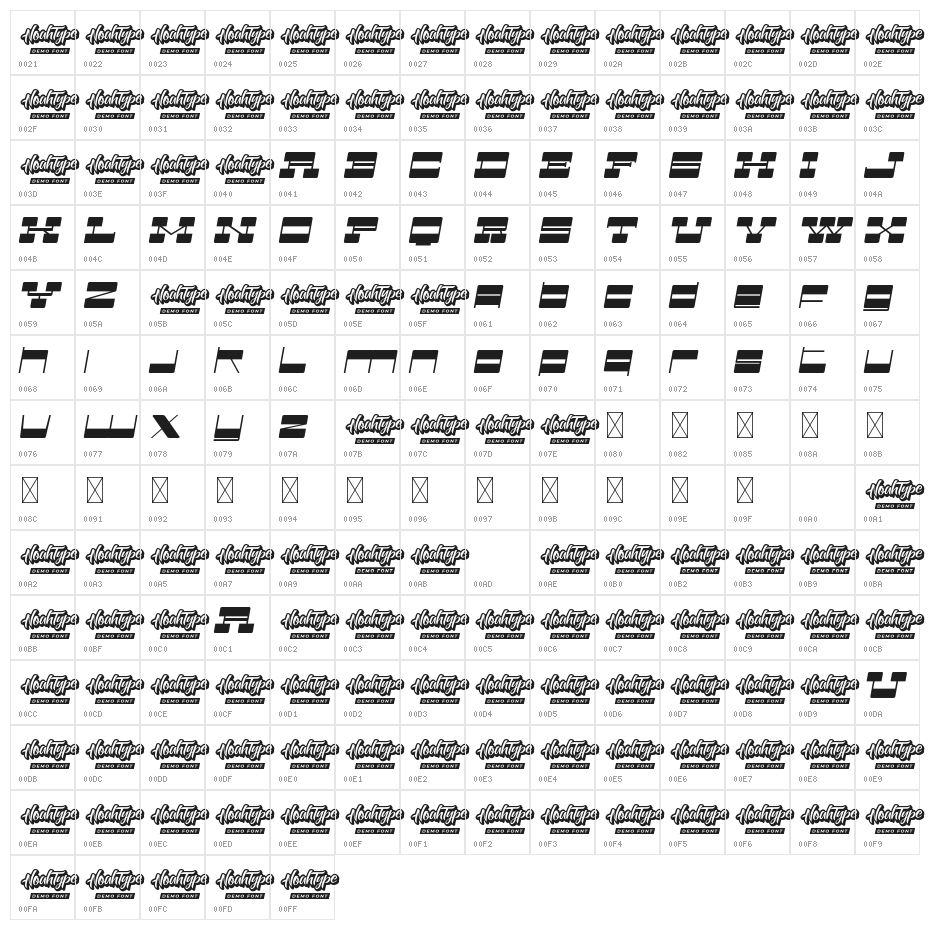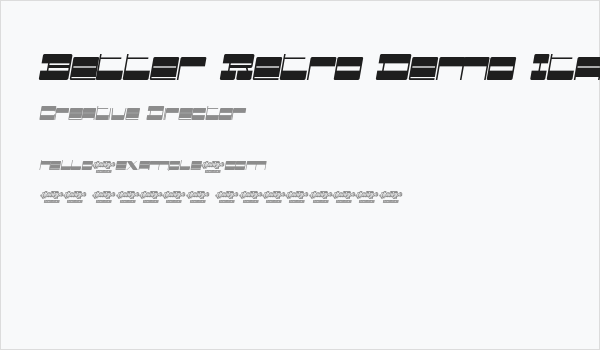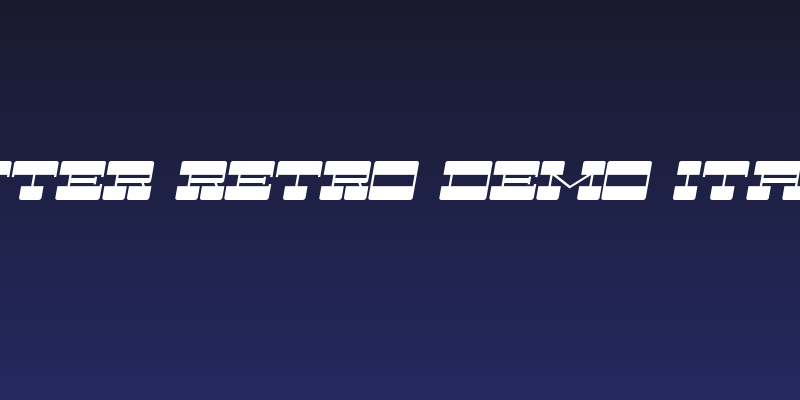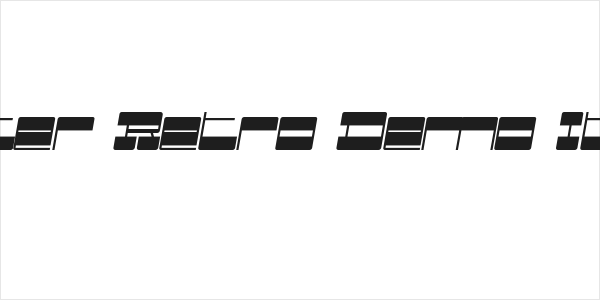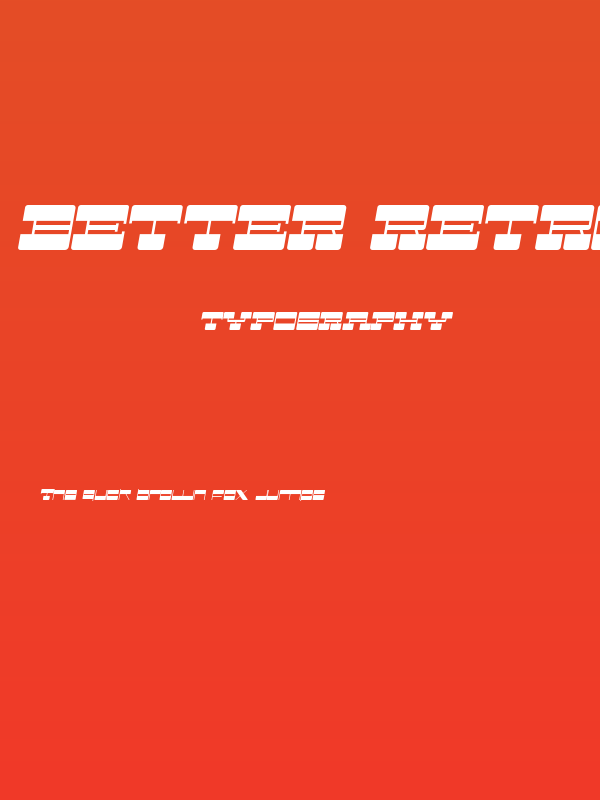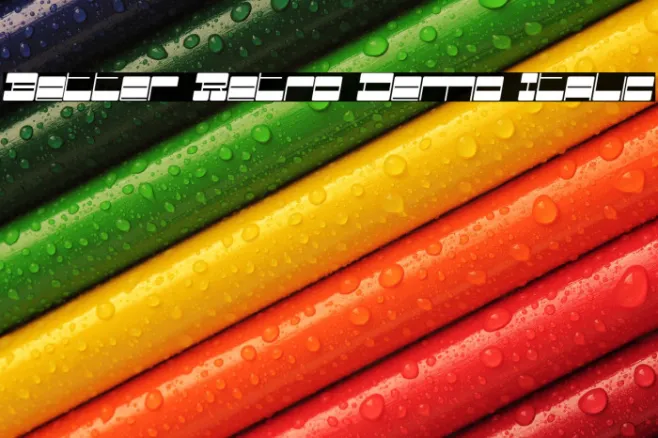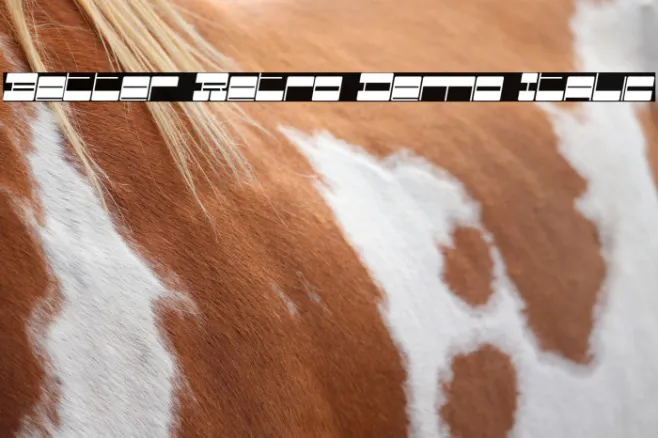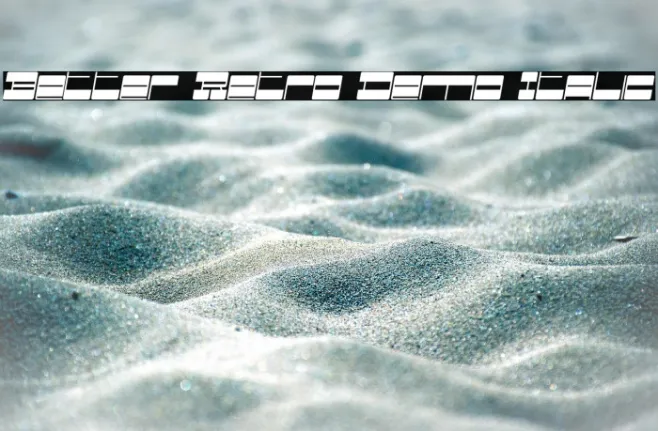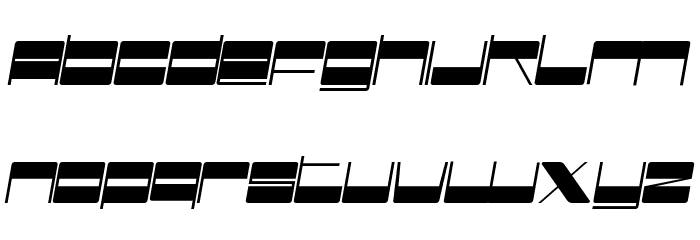
Better Retro Demo Italic Font
| Name | Better Retro Demo Italic |
| Schriften Familie | Better Retro Demo |
| Style | BetterRetroDemoItalic |
| Gewicht | Italic |
| Kategorien | Retro |
| Gesamtstil | Retro, Futuristic |
| Vorgeschlagene Projekte | Ideal for retro-themed posters, video game graphics, sci-fi book covers, and branding for tech products. |
Better Retro Demo Italic